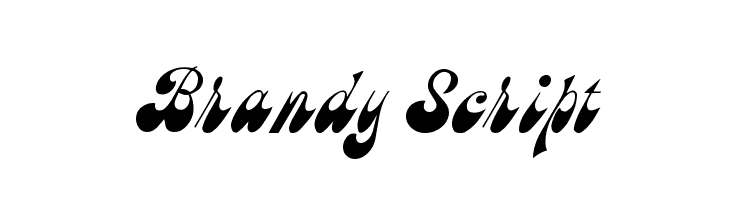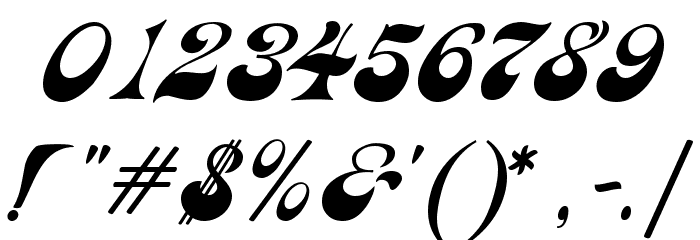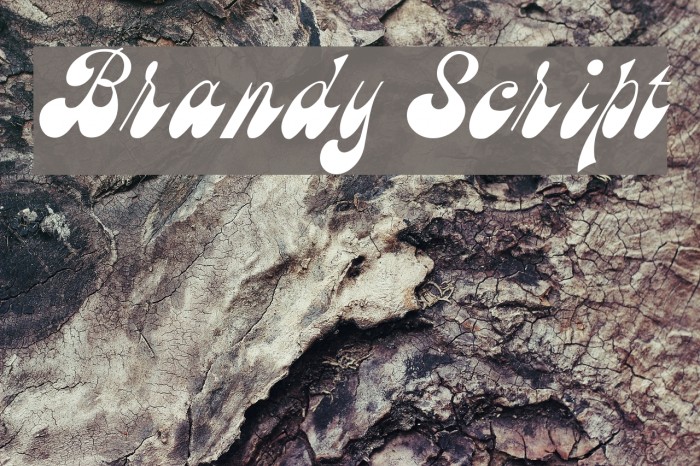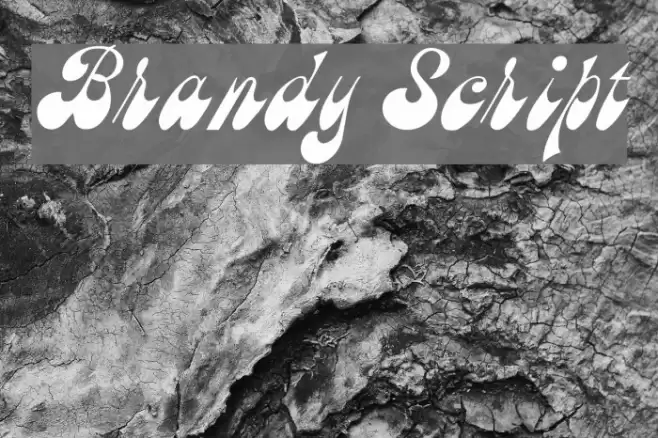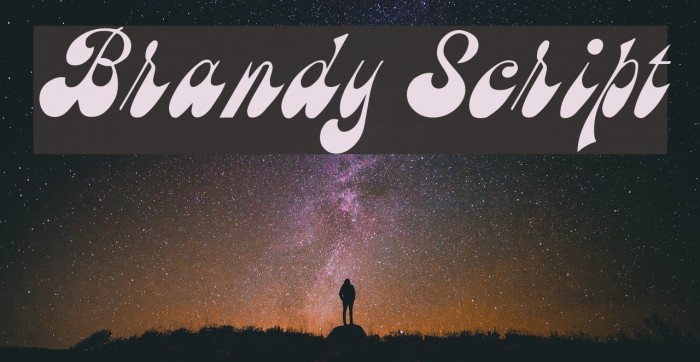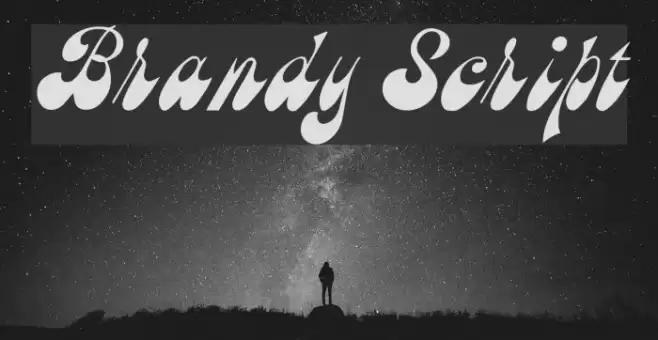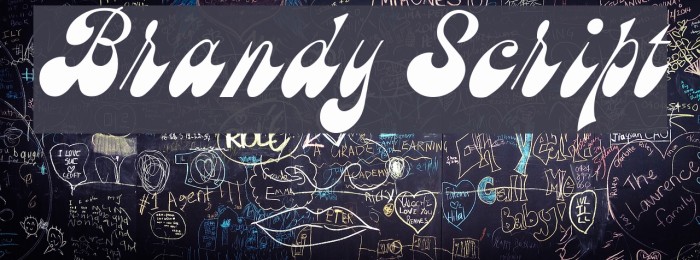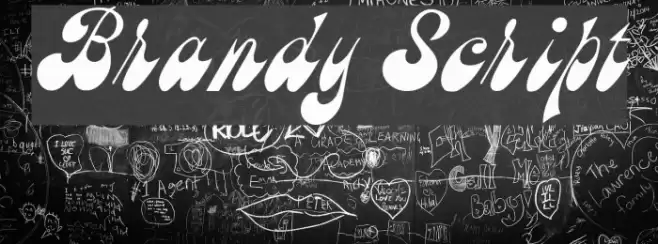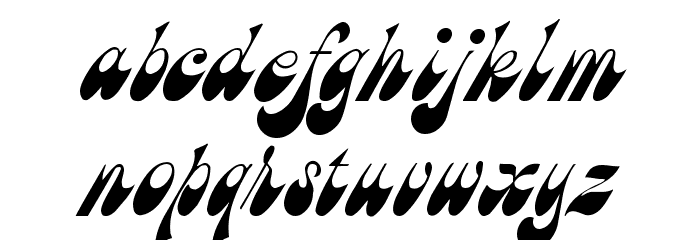
Brandy Script Font
Fonts by Rick Mueller
| Gesamtstil | Elegant, Decorative |
| Anwendungsfall | Logos, Invitations, Headlines |
| Vorgeschlagene Projekte | Ideal for wedding invitations, luxury branding, elegant packaging, and decorative headlines. |